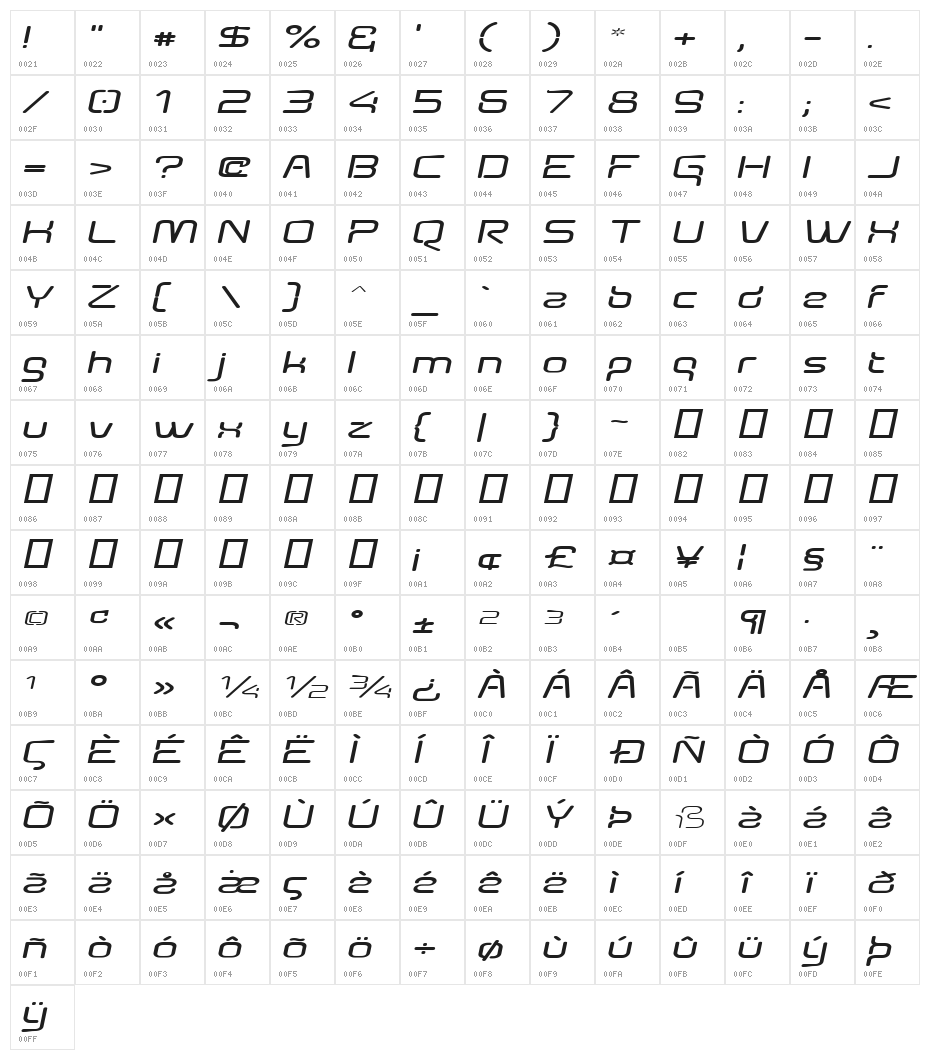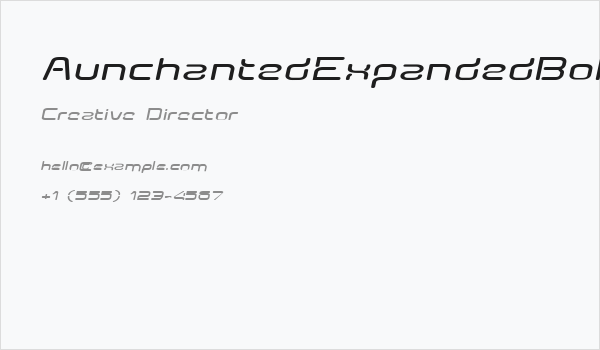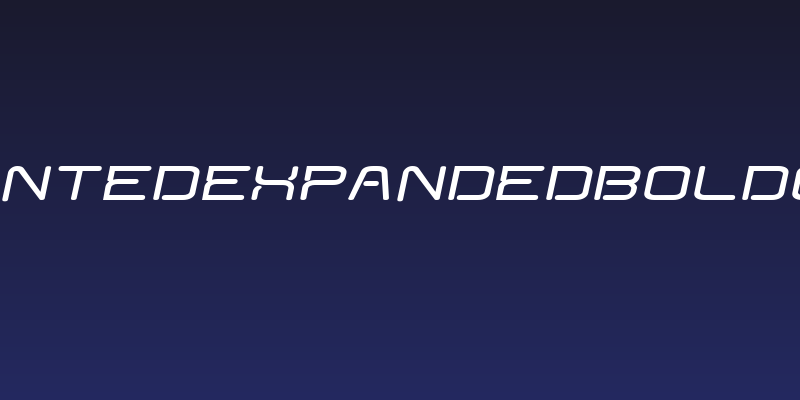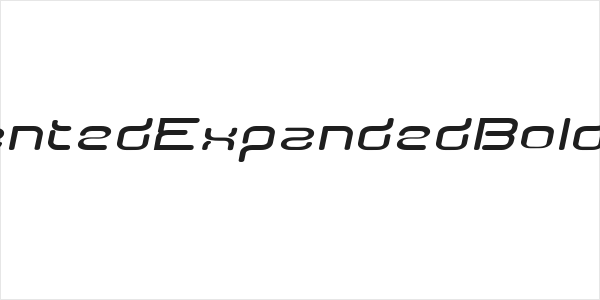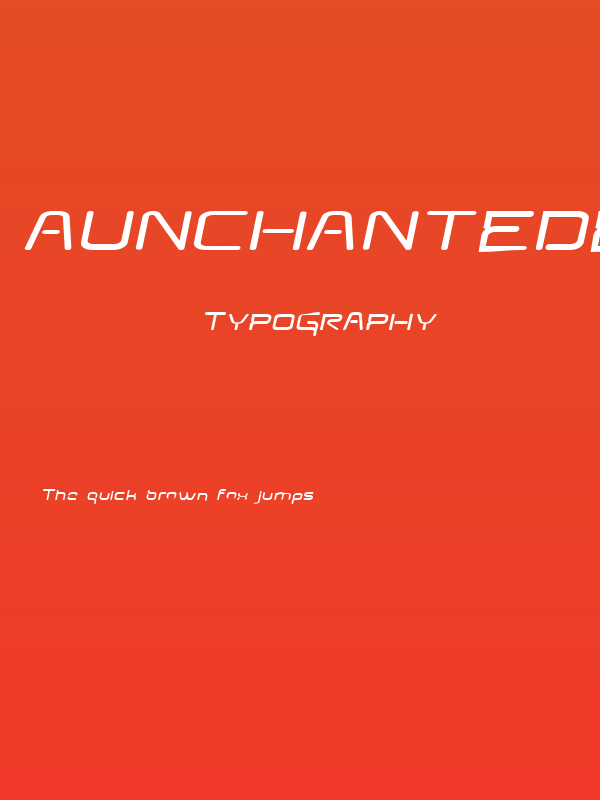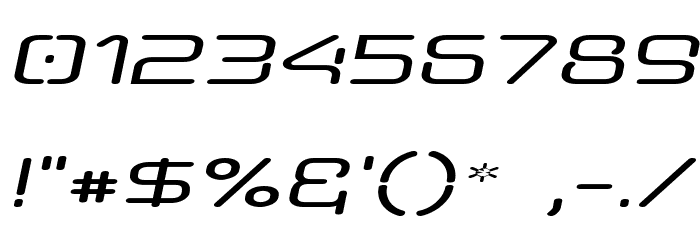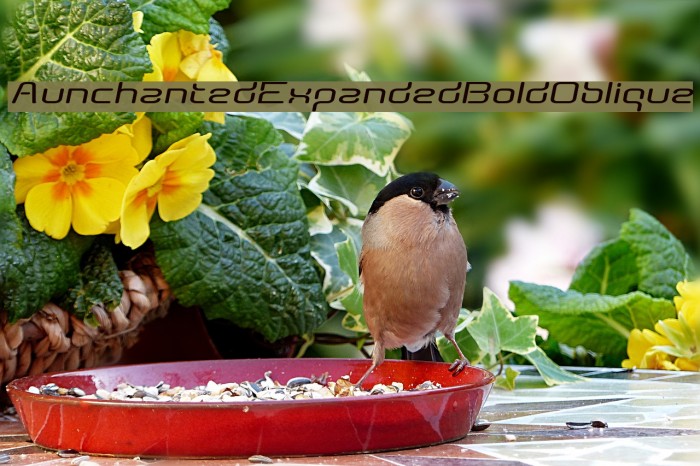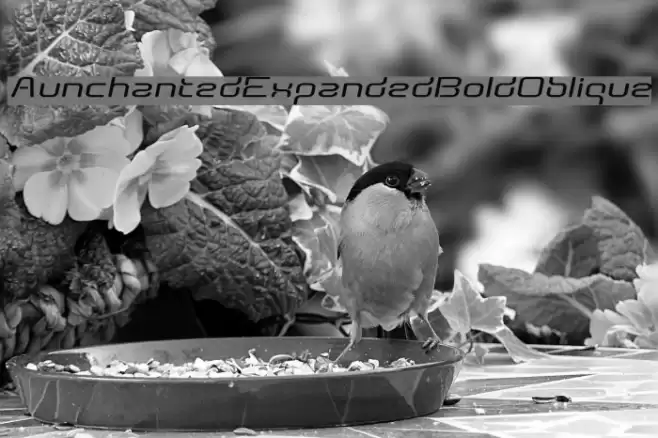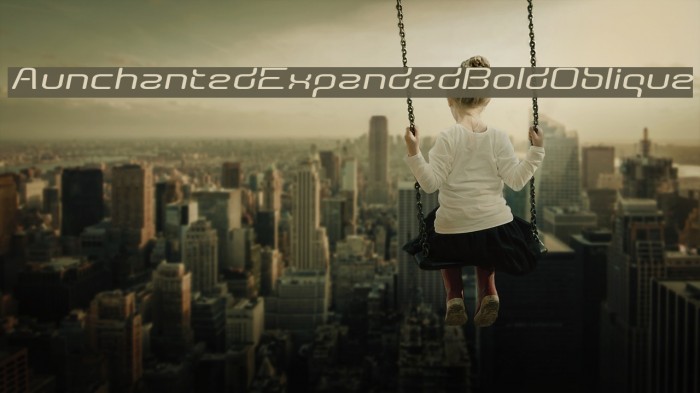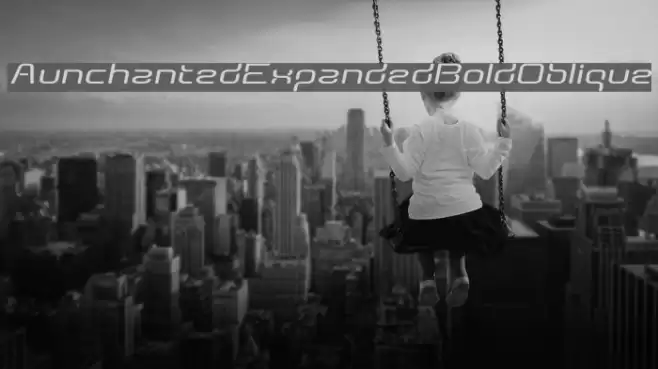
AunchantedExpandedBoldOblique Font
| Largura | Expanded |
| Projetos propostos | Ideal for technology branding, sci-fi movie posters, modern advertising, and innovative product packaging. |